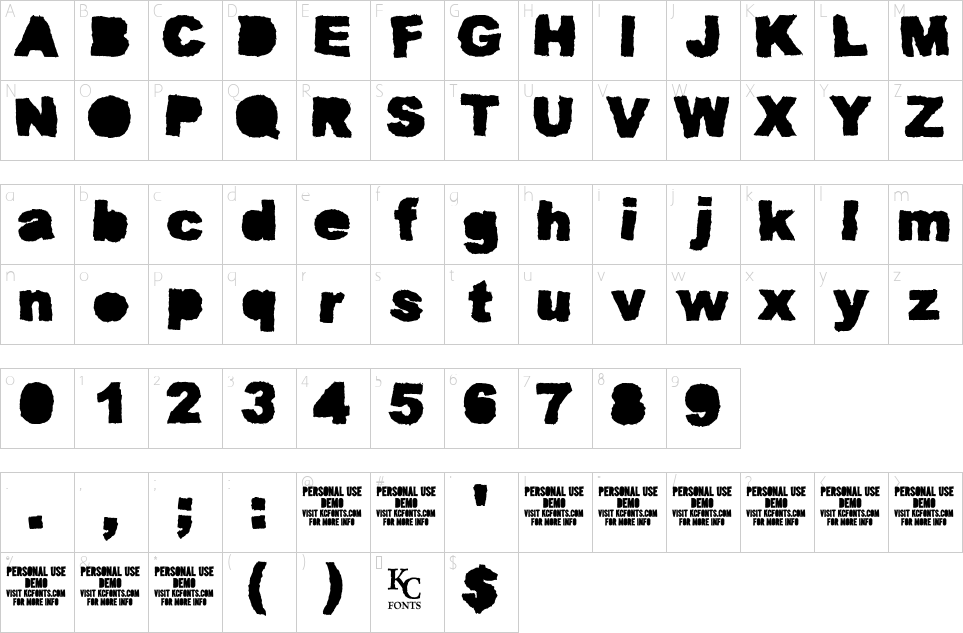
A fonte Muddy Tractor é uma escolha perfeita para criar textos cheios de personalidade, com um visual de caminhão de trabalhador encharcado no chão. Desenhada pela designer KC Fonts, essa fonte garante uma aparência não formal e informal, adequada para uma variedade de projetos, como design gráfico, ilustrações, e até mesmo para personalizar itens de colecionador. Com uma download de 4.683 vezes, é claro que os criadores da font Muddy Tractor encontraram a proporção certa de estilo e facilidade de uso. Se você está procurando por uma fonte que seja tanto um desafio quanto uma inspiração, a Muddy Tractor pode ser a fonte perfeita para sua próxima criação.